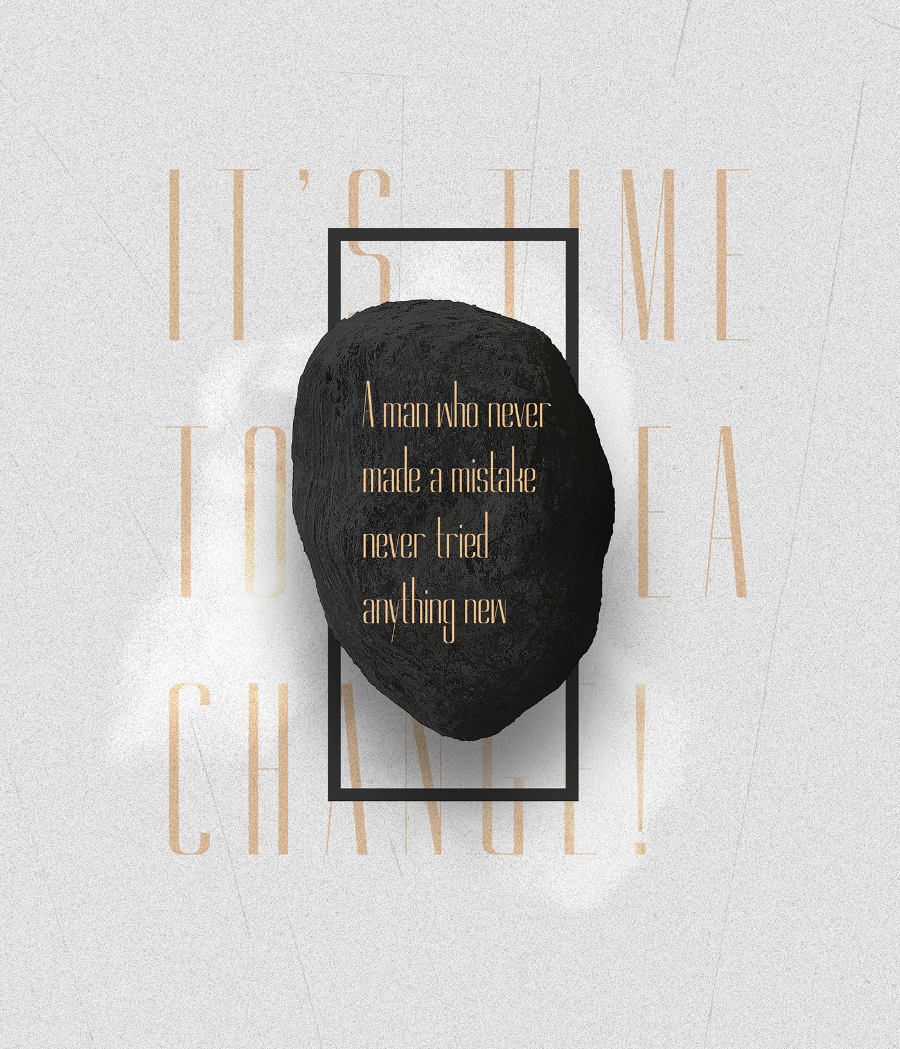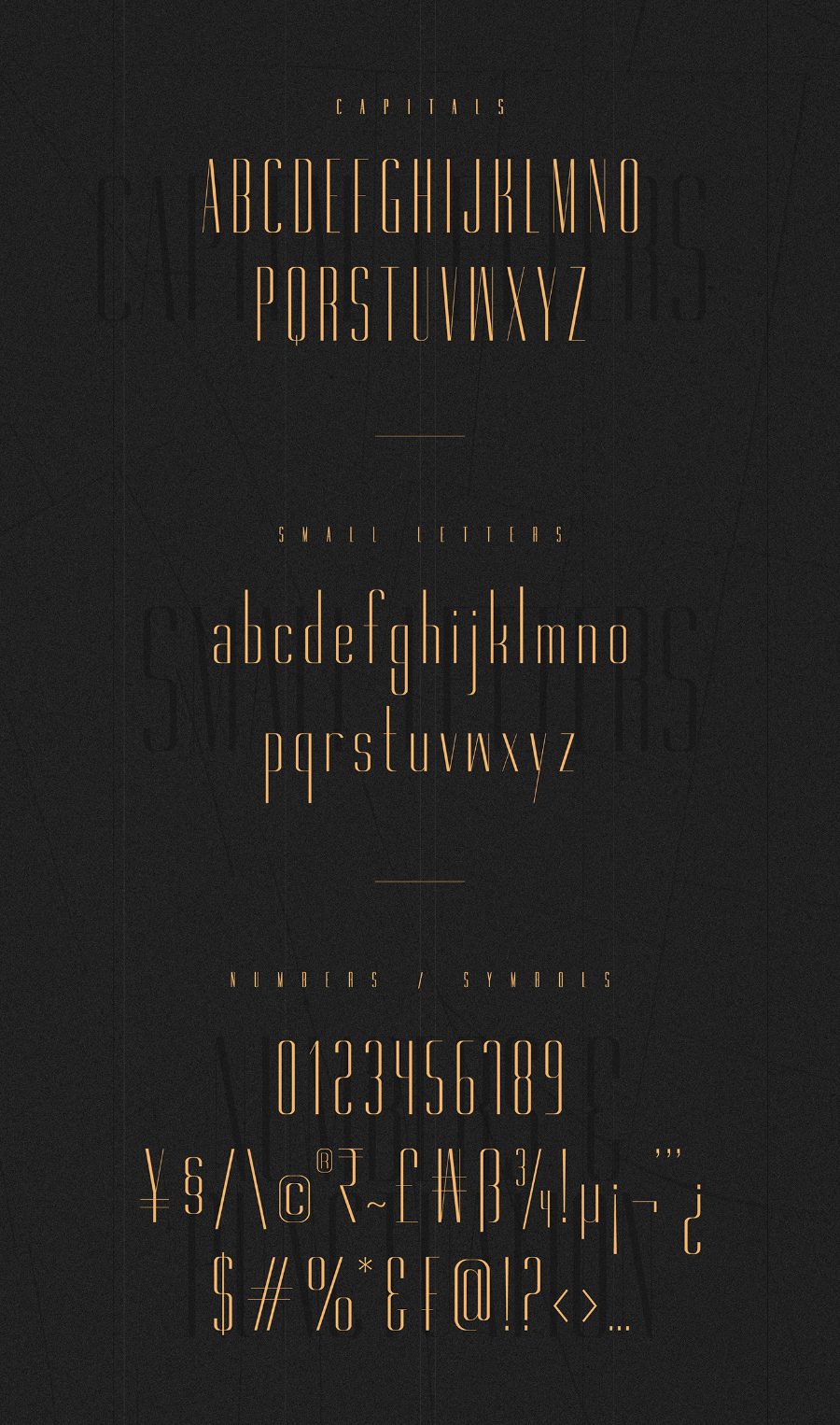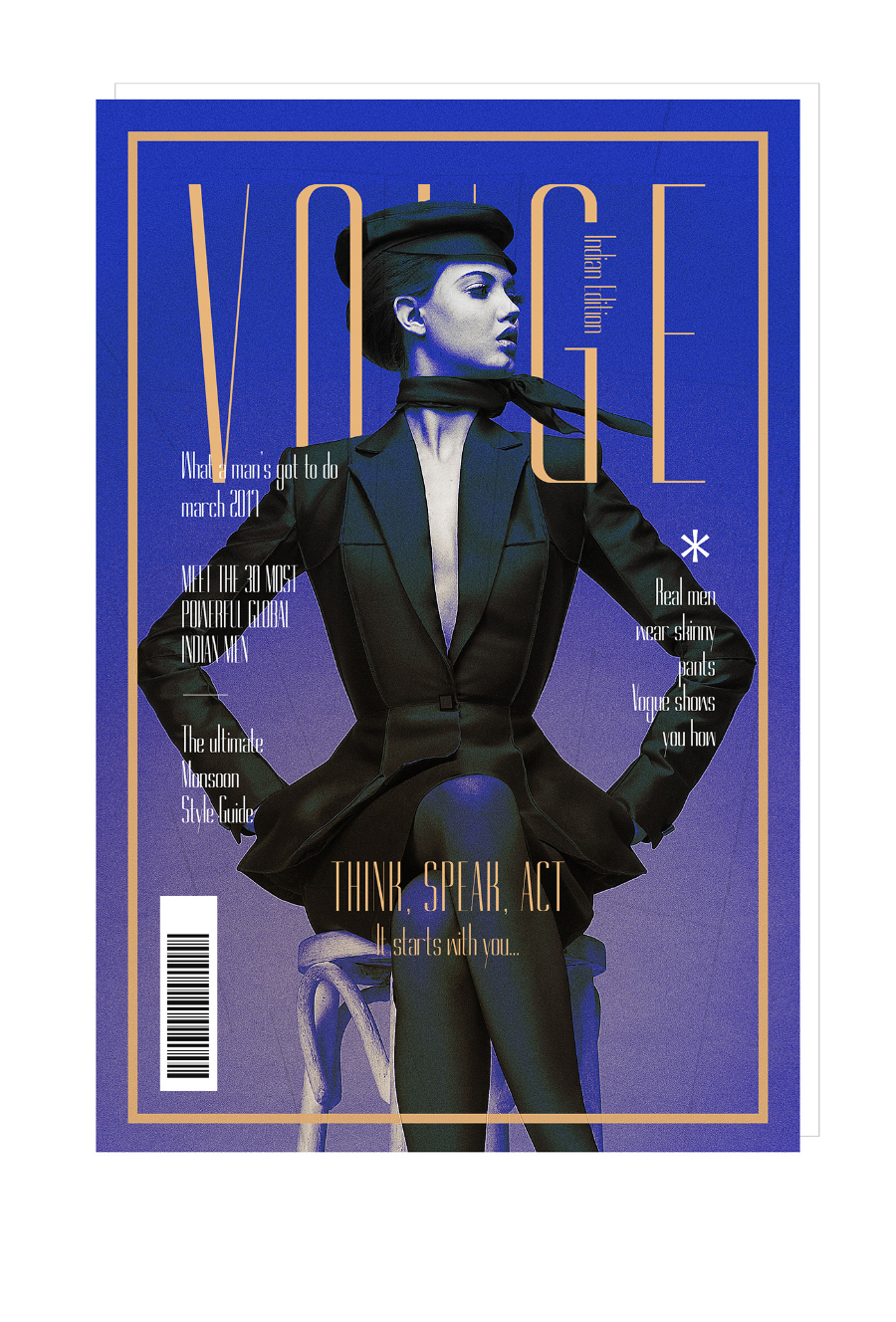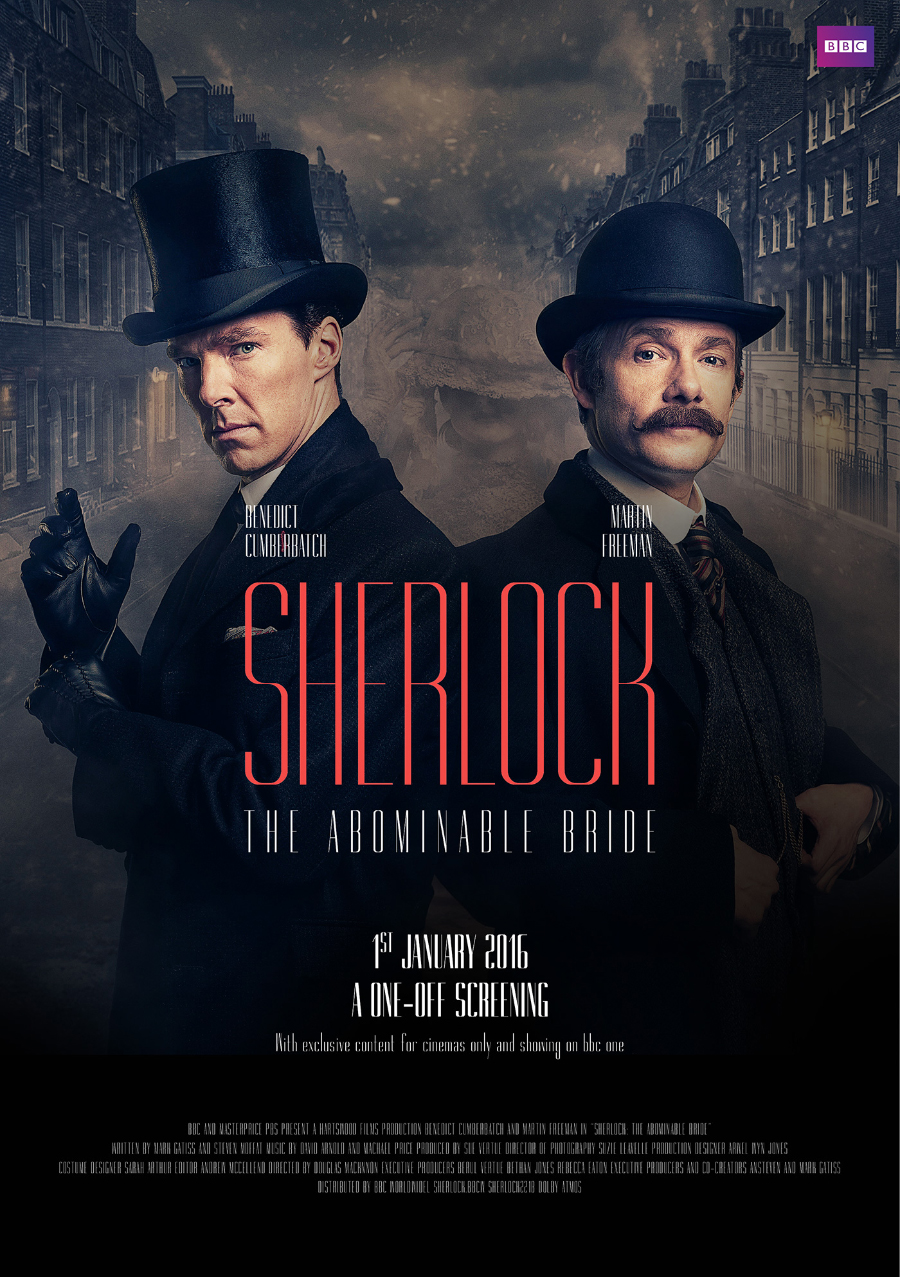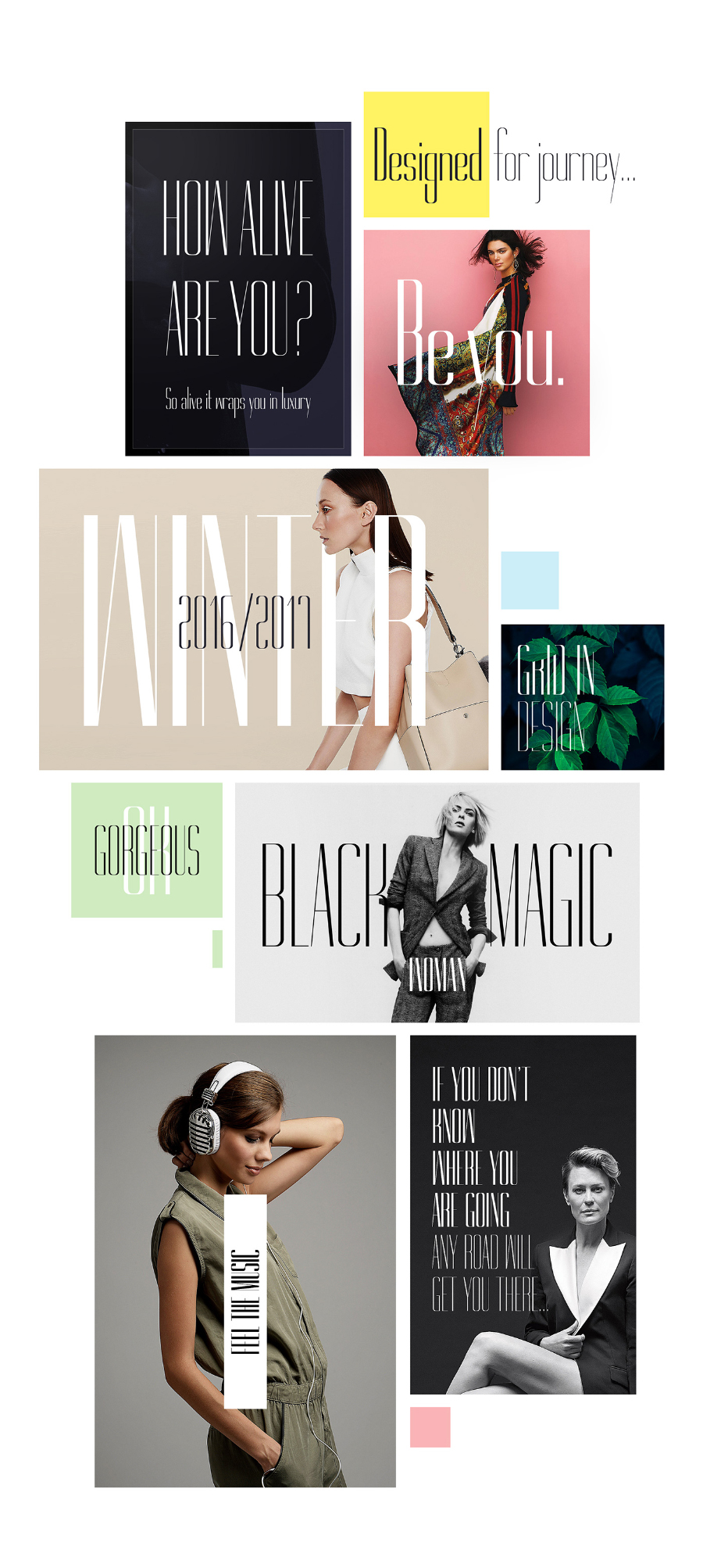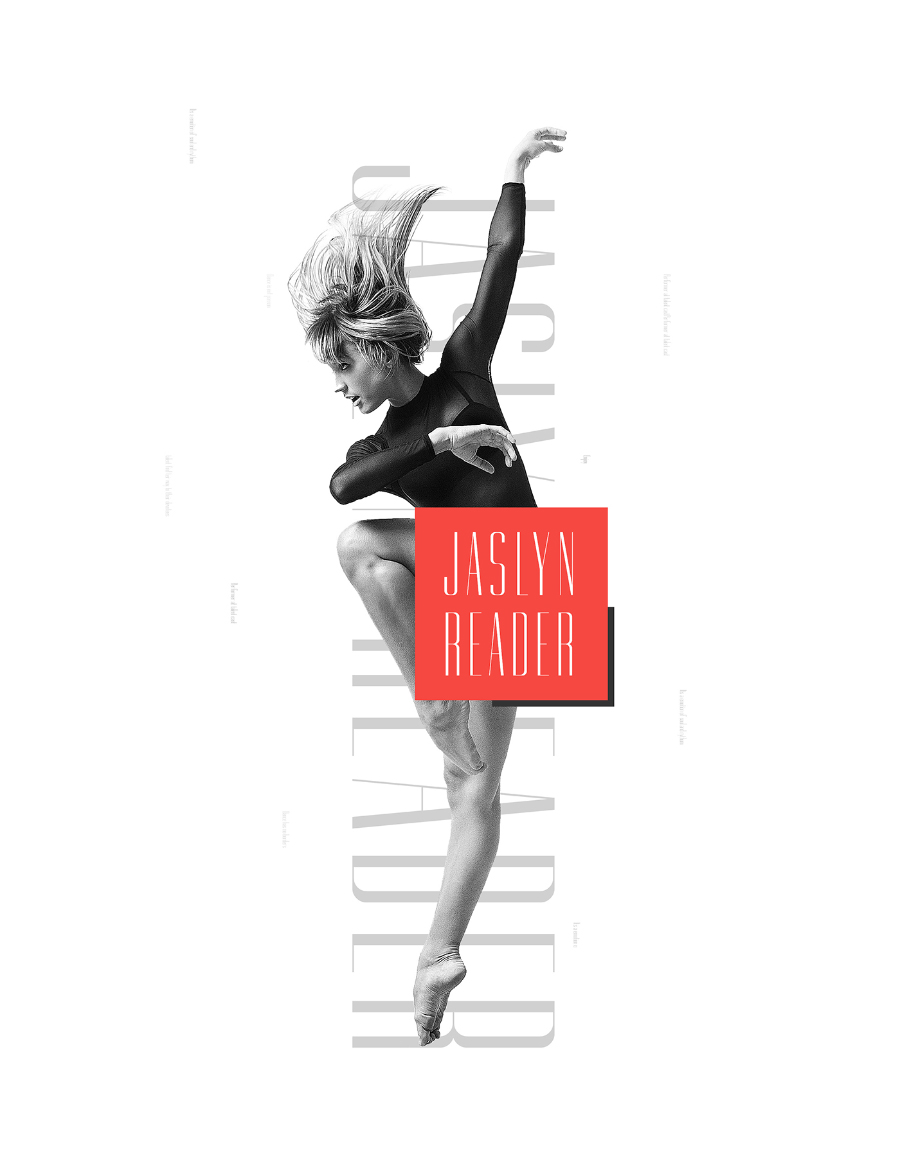
华丽的家庭免费演示
华丽的家庭免费演示是一个显示无重音浓缩型家庭有12个权重。在这里你可以从Regular,Medium,Bold,Thin,Light到Heavy。每种字体包含385个字形,其中包括小写字母和大写字母。另外,这个家庭还带有数字,标点符号和口音。凭借其重量的组合,这些字体将是伟大的,让您的设计醒目和现代的感觉。因此,这个家庭是理想的杂志,广告,时尚品牌和标志。